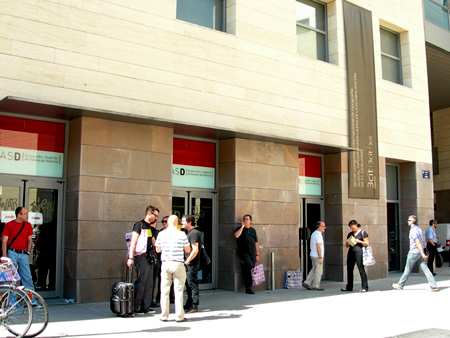
Se acaba de anunciar la convocatoria de comunicaciones para presentarlas al 4º Congreso Internacional de Tipografía que se celebrará, como viene siendo habitual, en Valencia en Junio de este año.
Es esta ocasión bajo el título de «La letra dibujada» el eje principal estará centrado en la relación del dibujo con la tipografía. Un debate muy interesante en un contexto digital que busca también en el trazo expresivo de la caligrafía nuevas vías de creación que han posibilitado el resurgimiento de la práctica de la escritura manual.
Nos parece muy interesante sobre todo, la relación entre el trazo libre y personal del dibujo de la letra con la regularidad y homogeneidad necesaria en una tipografía.
A este respecto, el tipógrafo inglés Walter Tracy nos dejó una frase que me parece muy acertada para definir uno de los posibles puntos de discusión y debate:
«La tipografía es un hermoso grupo de letras, no un grupo de letras hermosas».